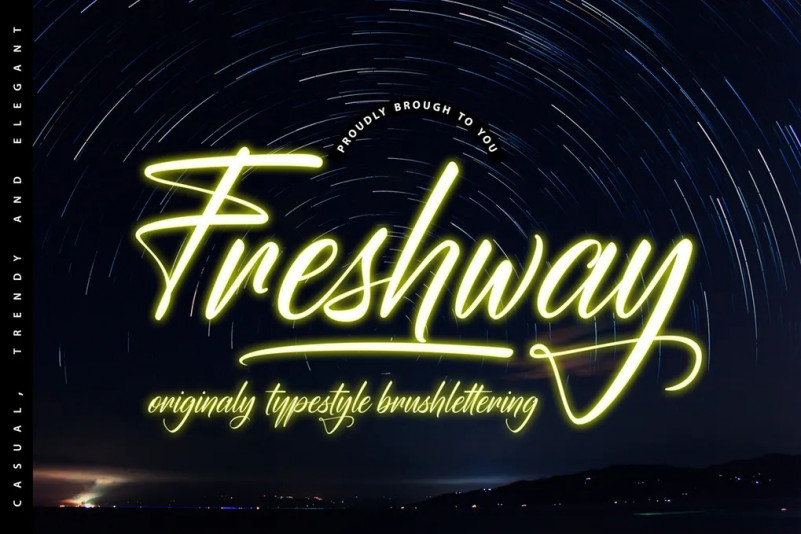
Freshway Font
Freshway Originaly Typetyle Font – est une nouvelle police qui est authentique et adaptée à beaucoup de vos besoins visuels, comme pour invitation, cartes de vœux, matériel de marque, cartes de visite, citations, affiches, et plus encore !
cette police Open Type fonctionnalités telles que Stylistic Sets, Stylistic Alternates, Contextuel Alternate, SWASH et Ligature. Les fonctionnalités Open Type sont accessibles à l’aide de programmes ouverts tels que Adobe Illustrator, Adobe InDesign, Adobe Photoshop Corel Draw X version et Microsoft Word. Et cette police a donné PUA unicode (Police spécialement codées). de sorte que tous les caractères alternatifs peuvent être facilement accessibles en entier